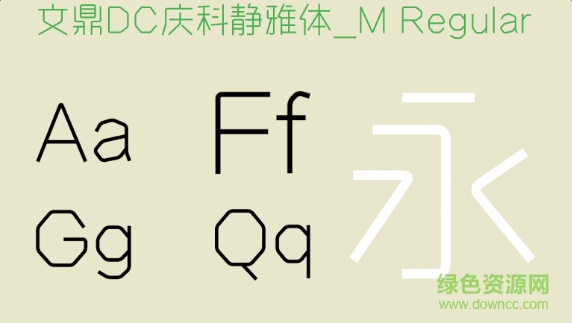
文鼎鄭慶科靜雅體
文鼎DC慶科靜雅體是文鼎字庫中的一款常用的廣告字體,這款字體轉(zhuǎn)角設(shè)計十分精巧,線條松緊適中,字形柔美而不失剛毅,喜歡這款字體的小伙伴快來綠色資源網(wǎng)下載吧!
文鼎慶科靜雅體字體介紹
文鼎DC慶科靜雅體,是一款黑體與綜藝體的結(jié)合體,字體筆畫美觀大方,字型特點是簡、直、連,具有較大范圍的應(yīng)用空間。適用于高端品牌廣告與平面設(shè)計。